テロップやWebなどに幅広く活用できる「モトヤフォント」の低価格フォントシリーズ「モトヤフォントlite」をオンライン限定で6月上旬より販売開始
モトヤは、文字種を限定した低価格商品「モトヤフォントlite」を2022年6月上旬より、ダウンロード限定で販売を開始したことを発表した。
「モトヤフォントlite」製品紹介
モトヤ書体の開発は1950年代から始まり、活字時代から現在のアウトラインフォントに至るまで「可読性」と「文字の美しさ」を追求されてきた。
印刷業界で絶大な支持を得てきたモトヤ書体は、近年では、テレビテロップやゲーム、Web、地図サイトなど幅広いジャンルに導入されるケースが増えている。
「モトヤフォントlite」は、文字種を改定常用漢字(2,136字)や人名用漢字(863字)などに限定した、低価格商品となる。
標準的な文章表現に使用できる必要最低限の文字種が収録されているので、YouTubeやTikTok配信者をはじめ、様々なシーンでクリエイティブな活動をされている人にとってもオススメ。
バラエティー豊かな10書体をラインナップ「モトヤフォントlite」
「モトヤフォントlite」では、クリエイティブなシーンでご使用いただけるUD書体やデザイン書体、筆文字書体などのバラエティー豊かな10書体をラインナップしている。
「モトヤフォントlite」UD書体
モトヤUD(ユニバーサルデザイン)書体は、大文字化対応や太さの調整、シンプルな文字構成で通常のフォントより可読性・視認性・判読性に優れており、様々な分野での活用が可能。
大手コンビニ弁当の商品情報のラベルにも採用されている、読みやすく見やすいモトヤのUD書体は各種施設の職員の方が作成される案内チラシやポスターなどにも最適。
「モトヤフォントlite」デザイン書体
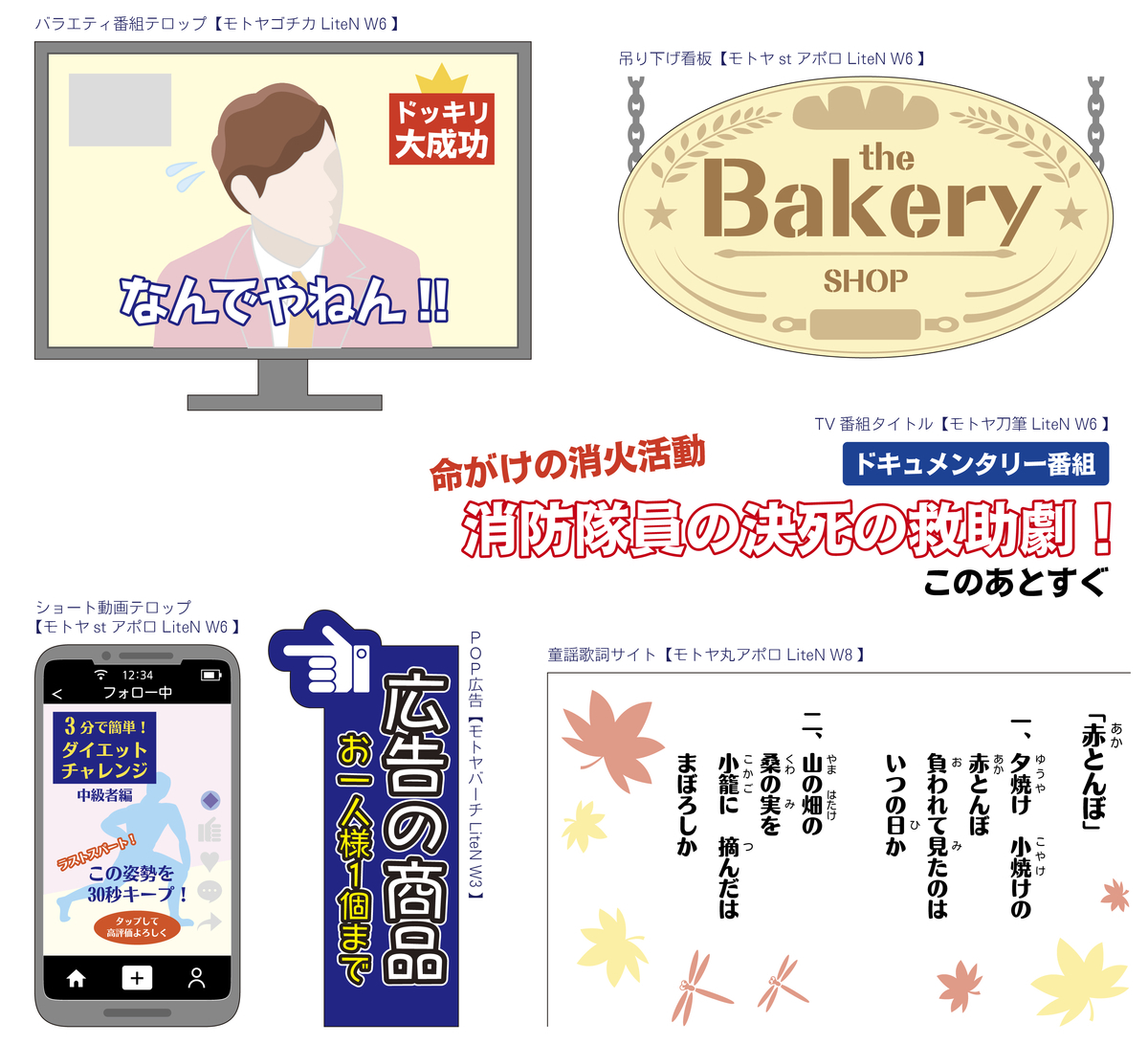
モトヤのデザイン書体には、バリエーション豊かな書体がラインナップされており、印刷はもちろん、Webや映像・動画(画像化して使用)にも使える分かりやすい使用許諾内容なので、YouTubeやTikTok配信者をはじめ、様々なシーンでクリエイティブな活動をされている人におすすめ。
「モトヤフォントlite」筆文字書体
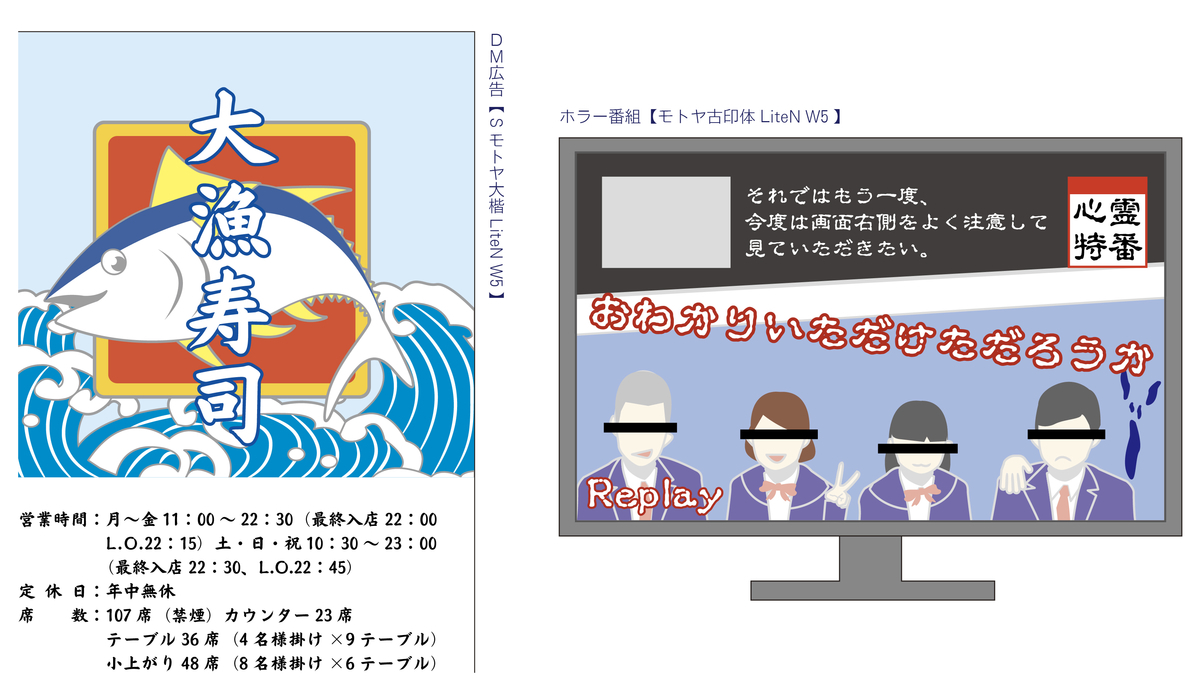
モトヤの筆文字書体は、プロの書家の監修により制作されており、伸びやかな筆使いや墨の香りがします。
テレビテロップや新聞紙面などにも採用実績があり、映像・動画(画像化して使用)やポスター・チラシのさらなるクオリティアップに役立つ。
「モトヤフォントlite」は、文字種を改定常用漢字や人名用漢字などに限定したモトヤ独自の文字セット(合計3,681文字)を採用しているため、収録していない文字を入力すると「〓」が表示され、文字化けによる印刷事故につながるので注意が必要。